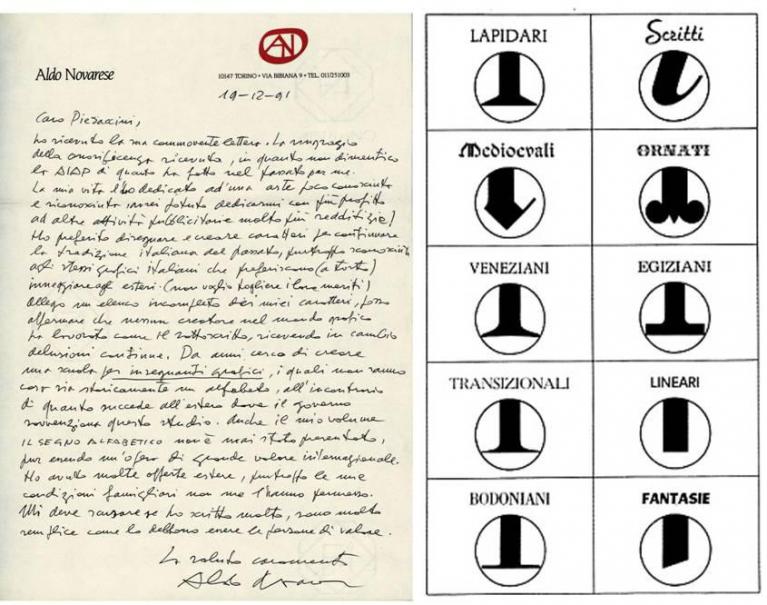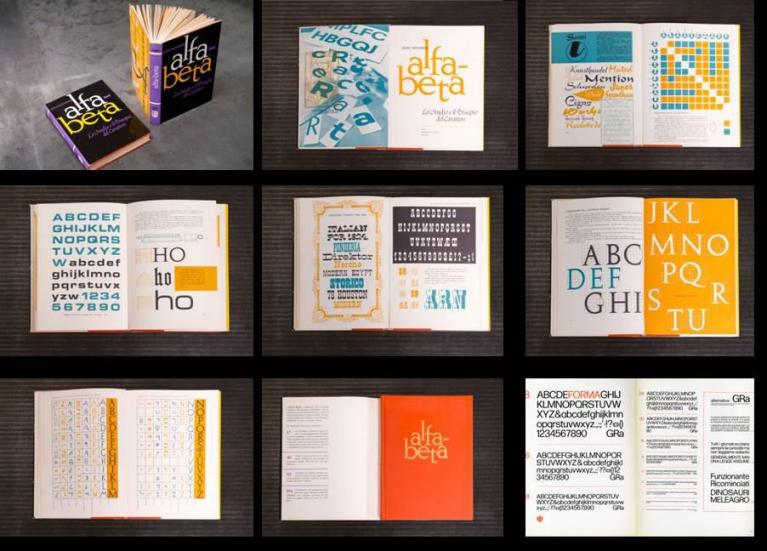
1920 – 2020 / Aldo Novarese: il più grande creatore di font
Fra i grandi disegnatori e inventori di caratteri per la scrittura artificiale, italiani sì ma di acclarata levatura internazionale, accanto a nomi mitici, come quello di Luca Pacioli, di Aldo Manuzio, di Francesco Griffo, di Panfilo Castaldi e di Giambattista Bodoni, spicca, per creatività e prolificità, quello di Aldo Novarese (1920-1995). A lui si deve, oltre al resto di cui di si dirà, il progetto di circa 200 famiglie di caratteri tipografici (font), dei quali una trentina per la Fonderia Nebiolo di Torino, dal 1880 al 1978 l'unica fonderia italiana di rilievo europeo, che insieme ai caratteri tipografici in piombo, produceva anche le macchine da stampa che li impiegavano.
Per l'elevato numero di font da lui creati, Aldo Novarese sarebbe degno di entrare nel Guinness World Records: a tale proposito, una classifica giapponese gli ha assegnato il primo posto fra i designer grafici di tutti i tempi e di tutto il mondo.
E allora, ecco l'Egizio (1955-58), un sobrio neretto da lui messo a punto in quattro anni di lavoro e di continue rettifiche per ottenere le grazie geometricamente il più precise possibile. L'Eurostile (1962), il suo must, derivato dal Microgramma, che aveva concepito in precedenza insieme al suo maestro, Alessandro Butti, comprensivo di ben 10 stili e 10 opzioni family package.
E poi c'è il fluido ed accurato Forma (1966-1967), sans-serif, frutto della collaborazione del nostro con una squadra di grafici stellati di scuola milanese, composta da Franco Grignani, Giancarlo Iliprandi, Bruno Munari, Ilio Negri, Till Neuberg, Alfredo Oriani e Pino Tovaglia, che la Nebiolo volle istituire per vincere, purtroppo senza lo sperato successo, la concorrenza straniera dell'Univers di Adrian Frutiger (del 1957 per Deberny & Peignot) ma soprattutto quella di Helvetica (entrambi i type derivati dall'Akzidenz Grotesk), il carattere creato da Hoffmann e Miedinger per la Haas, sempre nel 1957, che è tuttora leader incontrastato sulla piazza internazionale. Purtroppo il progetto del carattere Forma, ad opera del team di grafici, che aveva preso il nome di Nebiolo Research Group, si è rivelato un esperimento non riuscito.
“Esempio paradigmatico dell'incomunicabilità dei due mondi è il Forma. [...] L'idea sarebbe stata quella di unire le rispettive competenze, ma il risultato è l'impossibilità di un dialogo tra la cultura tecnica della tradizione tipografia – Novarese – e la cultura del disegno industriale, egemone e di successo, ma di fatto incompetente sulle problematiche del progetto tipografico." (Piazza, Sfligiotti).
Che questa dicotomia fra type designer e graphic designer potesse essere insanabile lo aveva già intuito Franco Grignani, fin dal primo incontro fra la Nebiolo, con Aldo Novarese, e i grafici milanesi, avvenuto a Torino nel maggio 1965. Così egli aveva infatti dichiarato:
"Per me c'è questo divario tra la tua arte [si rivolgeva a Novarese], che è vicina alla tipografia tradizionale, e la nostra che è invece vicina a questioni estetiche [...] Chi disegna solo alfabeti potrebbe non conoscere i segreti di una parte del mondo che si occupa invece di altri problemi visivi."
Tuttavia, nonostante il suo pallido successo commerciale, sotto il profilo culturale il carattere Forma si è comunque guadagnato importanti riconoscimenti: nel 1970 ha infatti ottenuto una menzione speciale al Compasso d’Oro e, sempre nel '70, anche quella del Gute Form, l'annuale premio promosso dall'Internazionale Design-Zentrum di Berlino.
Se Forma non è stato quell'asso pigliatutto che Nebiolo e il team si auguravano di aver sfoderato per sbaragliare il mercato, la straordinaria collaborazione fra i maestri della Grafica, durata spontaneamente dal 1965 al 1978, ha generato (non senza travaglio) il font Modulo che nel 1979 si è aggiudicato il Compasso d'oro. Del collettivo di lavoro, composto da Luciano Agosto, Giovanni Brunazzi, Franco Grignani, Giancarlo Iliprandi, Bruno Munari, Ilio Negri, Gianni Parlacino, Pino Tovaglia, cui si era aggiunto Armando Testa per la grafica pubblicitaria, non faceva ormai più parte Aldo Novarese, chiamatosi fuori nel 1974, tanto dalla squadra di lavoro, quanto dalla stessa Nebiolo. Le continue discussioni interne al gruppo e la messa in ombra della sua autorità, di lui che alla Nebiolo era sempre stato l'unico leader, avevano esaurito la sua capacità di sopportazione e, sebbene fosse timido, all'età di 54 anni aveva trovato la forza e il coraggio di mollare tutto e di ricominciare da capo, tout seul.
Nel 1966, il Magister – vedi foto – era invece stato la risposta vincente di Novarese/Nebiolo al Times New Roman di Stanley Morison e Victor Lardent, creato nel 1931, per Monotype.
Di discreto successo di marketing, Novarese aveva poi già anche creato per Nebiolo il Garaldus (1956), classico con le armoniose grazie, adatto a testi editoriali, e, ancor prima, c'erano stati il Juliet (1954-55), un elegante corsivo inglese, e il Recta (1958) – vedi foto –, ricco di variazioni seriali. Poi, quasi come per il gran finale di uno spettacolo pirotecnico, Novarese aveva creato per Nebiolo il fantasioso Stop (1970-71), il meno "tipografico" dei suoi alfabeti, "che centra in pieno il bersaglio di un carattere logografico, con un successo popolare e planetario che non accenna a scemare; l’egizio Dattilo (1974), la sua ultima creatura per la Nebiolo [in collaborazione con il team di graphicstar], chiude una dedizione quarantennale con il sapore sarcastico del tipo da macchina da scrivere." (Polano)
L'ITC Novarese (1978) è invece un suo personale best seller, che egli ha messo a punto, lasciatasi la Nebiolo alle spalle, per la newyorkese International Typeface Corporation, "originalissimo nel corsivo, perché ne riprende la matrice cancelleresca, la quale anticamente conservava in tondo le lettere maiuscole della capitalis romana. Il Nadianne [per la statunitense Monotype], dove Novarese riesce a fondere il ritmo delle antiche cancelleresche con l'agilità quasi sensuale di uno scritto nitido e deciso" (Aiap).
Questo è solo un breve elenco dei caratteri creati da Aldo Novarese, troppo esiguo lo spazio di un articolo per menzionarli tutti e molte ancora le cose da raccontare su di lui.
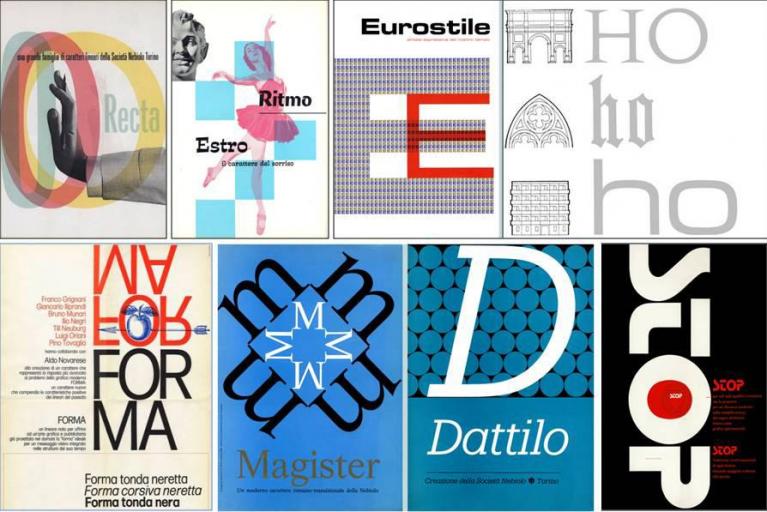
Alcuni dei font disegnati da Aldo Novarese. Da sinistra: Recta (1958); Estro, 1961; Eurostile, 1962; il carattere Eurostile accostato al linguaggio architettonico, pagina che compare nel volume di Novarese Il Segno alfabetico (1971), con questa didascalia: "la forma quadrata è l'espressione tipica dell'architettura del XX secolo, come dalla forma dell'arco a tutto sesto proviene la lapidaria romana ed da quella dell'arco ogivale traggono origine, a loro volta, le lettere gotiche”. Forma, 1966-1967 (con Franco Grignani, Giancarlo Iliprandi, Bruno Munari, Ilio Negri, Till Neuberg, Alfredo Oriani e Pino Tovaglia). Entrambi per la Fonderia Nebiolo. (Tipoteca Italiana); Magister, 1966; Dattilo, 1974 (con il Gruppo di Ricerca Nebiolo, cui si aggiunse Armando Testa per la grafica pubblicitaria); Stop, 1970-71.